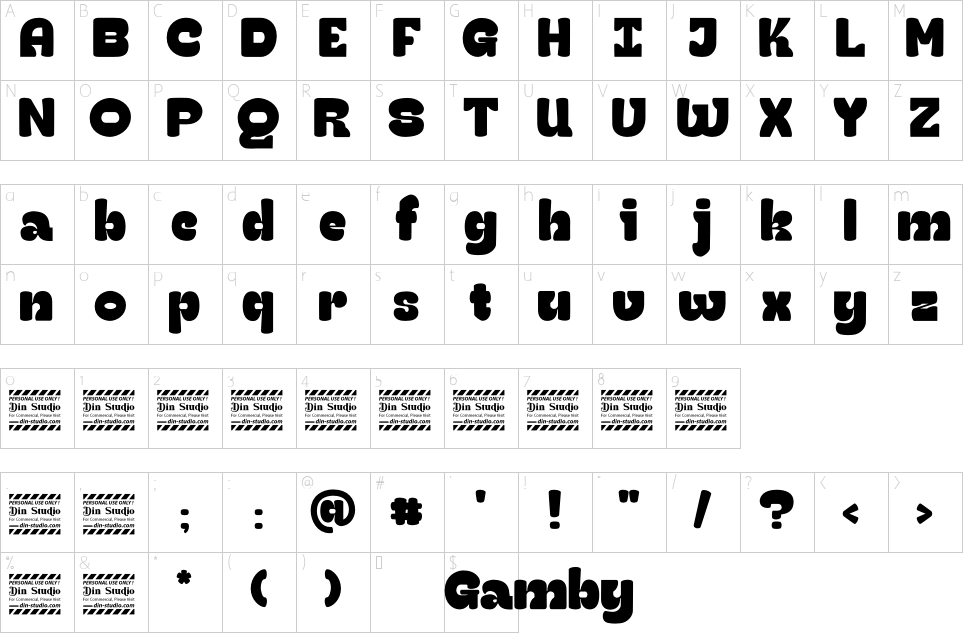
Gamby Font – Download Grátis
A Gamby Font é uma opção fresca e elegante para designers que estão procurando por uma fonte grátis para suas criações digitais. Arquitetada pela Din Studio, esta fonte é ideal tanto para projetos de computador Windows quanto Mac. O design desta fonte destaca-se por sua simplicidade moderna e capacidades visuais atraentes. Ela já foi baixada por 2,425 usuários, o que sugere seu grande valor como uma opção gratuita para qualquer designer buscando um estilo arrojado. A Gamby Font é perfeita para criar interfaces de usuário modernas, materiais de design gráfico ou simplesmente textos bonitos e minimalistas sem precisar pagar por licenças. Com ela em sua biblioteca de fontes gratuitas, você pode explorar seu poder de personalização sem comprometer o estilo profissional de seus projetos.